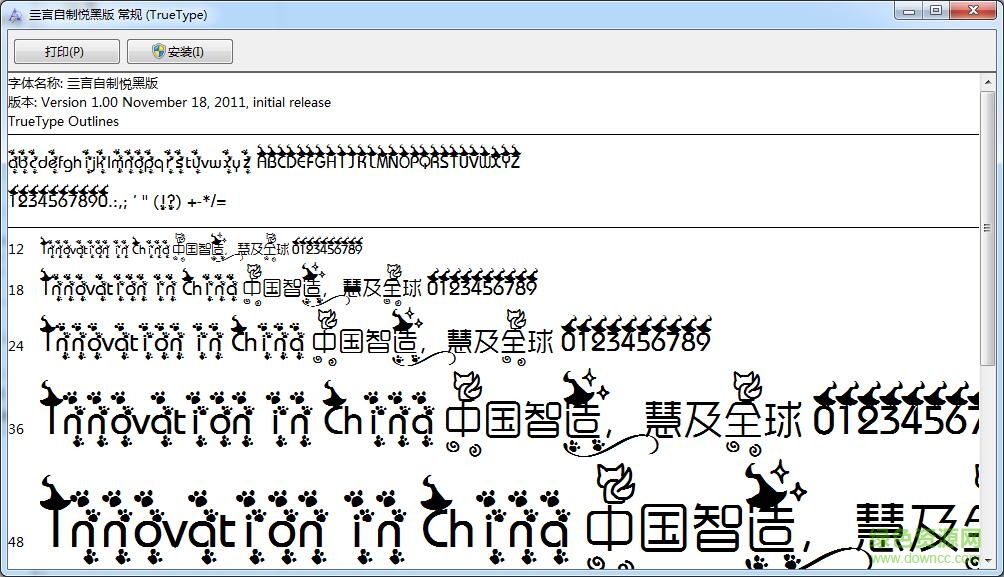
時光女與貓字體是一款免費的貓咪字體。少女心比較強的網(wǎng)友相信你一定會愛上這款字體的,字體呆萌,不是可愛!算是可愛字體中的一種吧!歡迎網(wǎng)友們下載使用。
時光女與貓字體是小編比較喜愛的一款字體!這款字體非常有個性,簡體的字體通過貓咪爪的點綴變得生動起來,在設(shè)計行業(yè)很受歡迎!